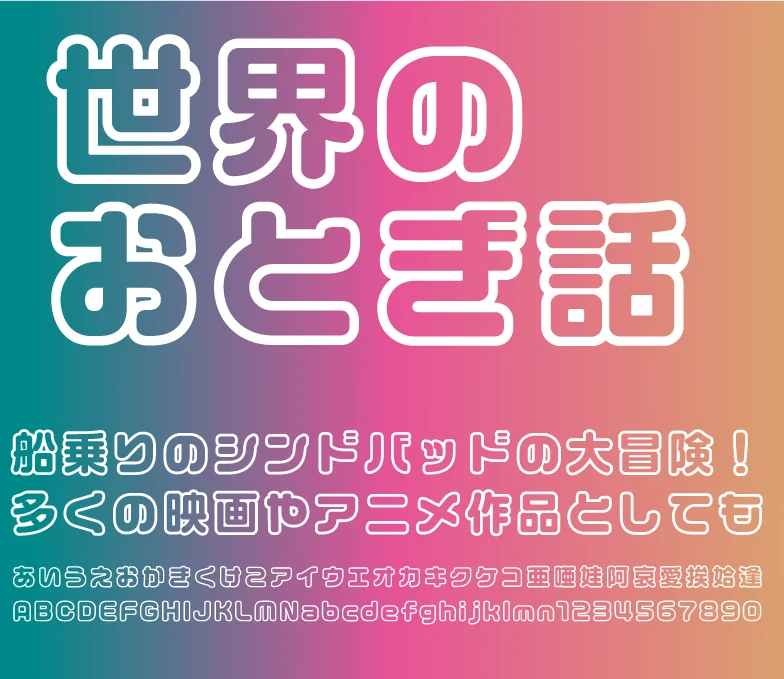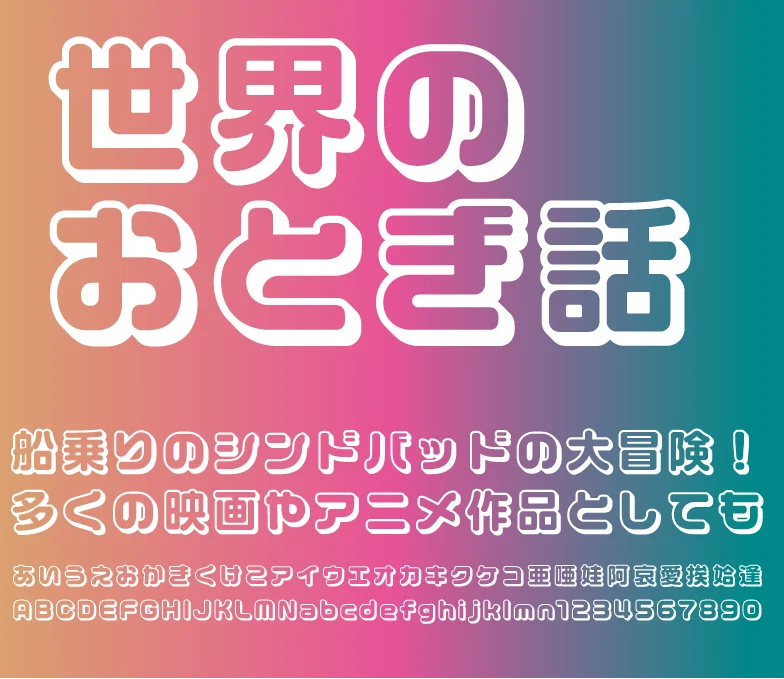
ロゴ丸Jr-popの特徴
「ロゴ丸Jr-pop」は、「ロゴ丸Jr」のデザインをベースに生まれた装飾書体です。文字の輪郭線のみを強調したデザインの「ロゴ丸Jr-pop-FutoLine」と、文字の背後に影を落とし立体的なデザインに見せる効果を持つ「ロゴ丸Jr-pop-Shadow」があります。
日本語フォントとしては数少ない装飾書体で、文字数も9,354文字と充実。実用性も十分です。(Adobe-japan 1-3準拠)
ロゴ丸Jr-popの特徴
「ロゴ丸Jr-pop」は、「ロゴ丸Jr」のデザインをベースに生まれた装飾書体です。文字の輪郭線のみを強調したデザインの「ロゴ丸Jr-pop-FutoLine」と、文字の背後に影を落とし立体的なデザインに見せる効果を持つ「ロゴ丸Jr-pop-Shadow」があります。
日本語フォントとしては数少ない装飾書体で、文字数も9,354文字と充実。実用性も十分です。(Adobe-japan 1-3準拠)
●FutoLine
ロゴ丸Jr-pop-FutoLine
●Shadow
ロゴ丸Jr-pop-Shadow